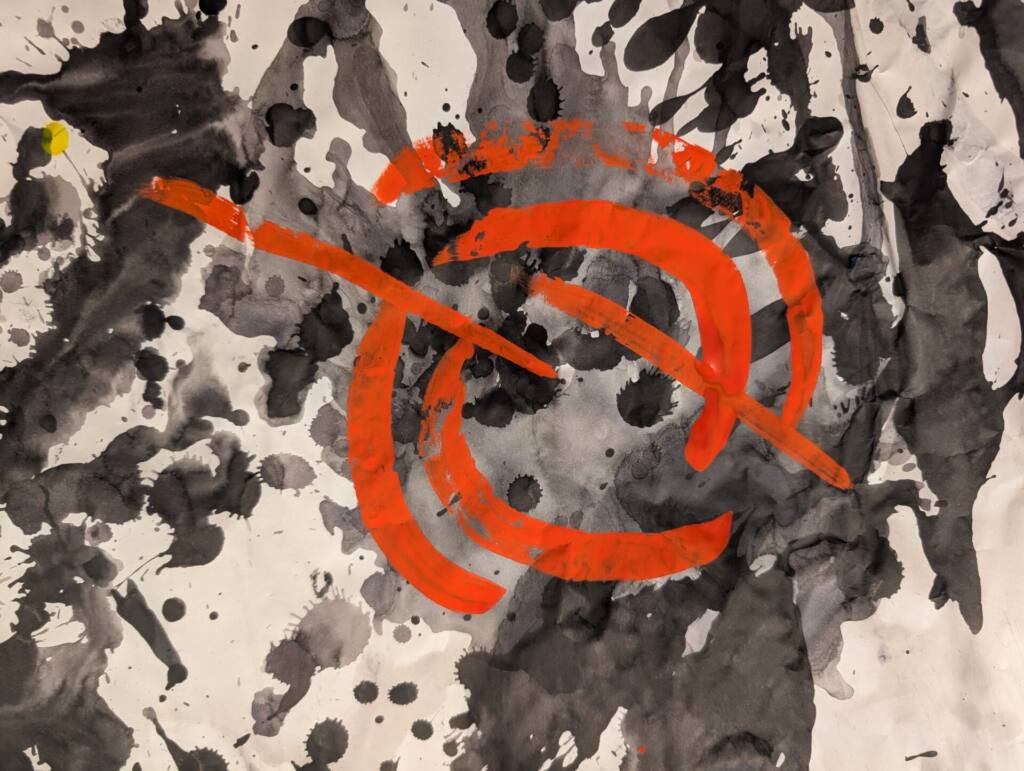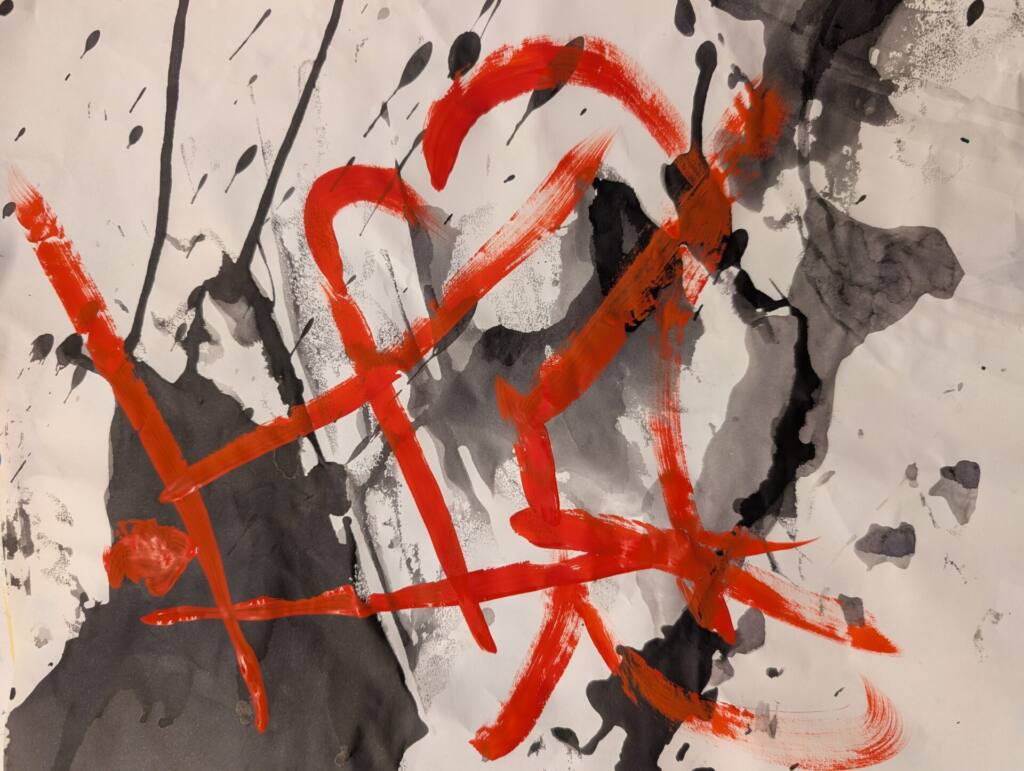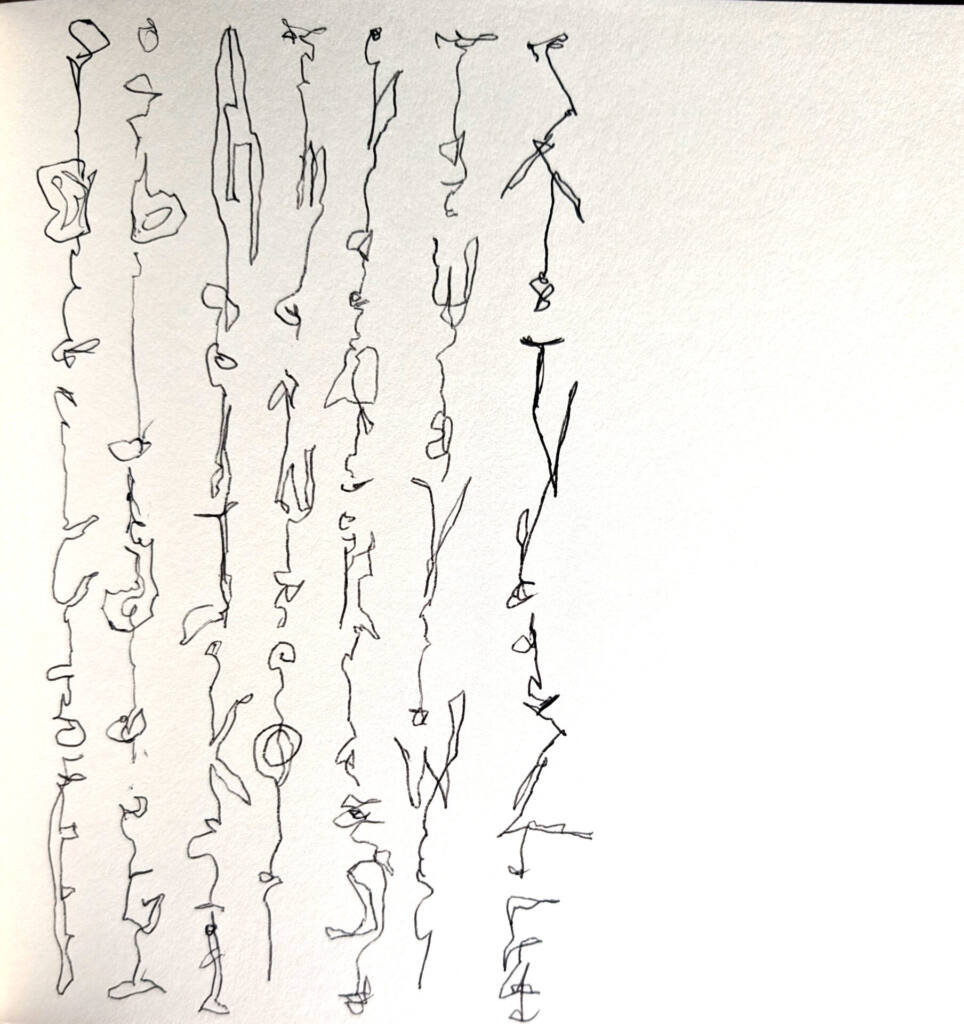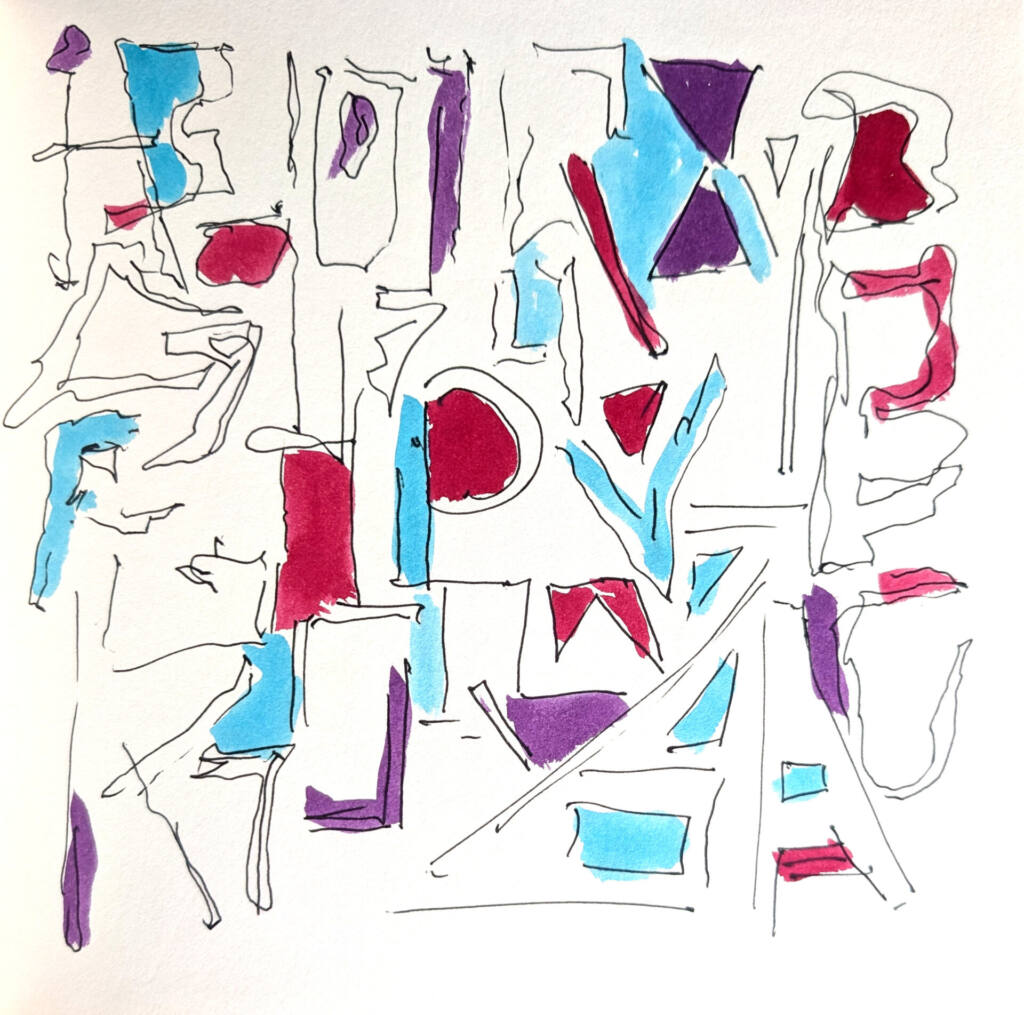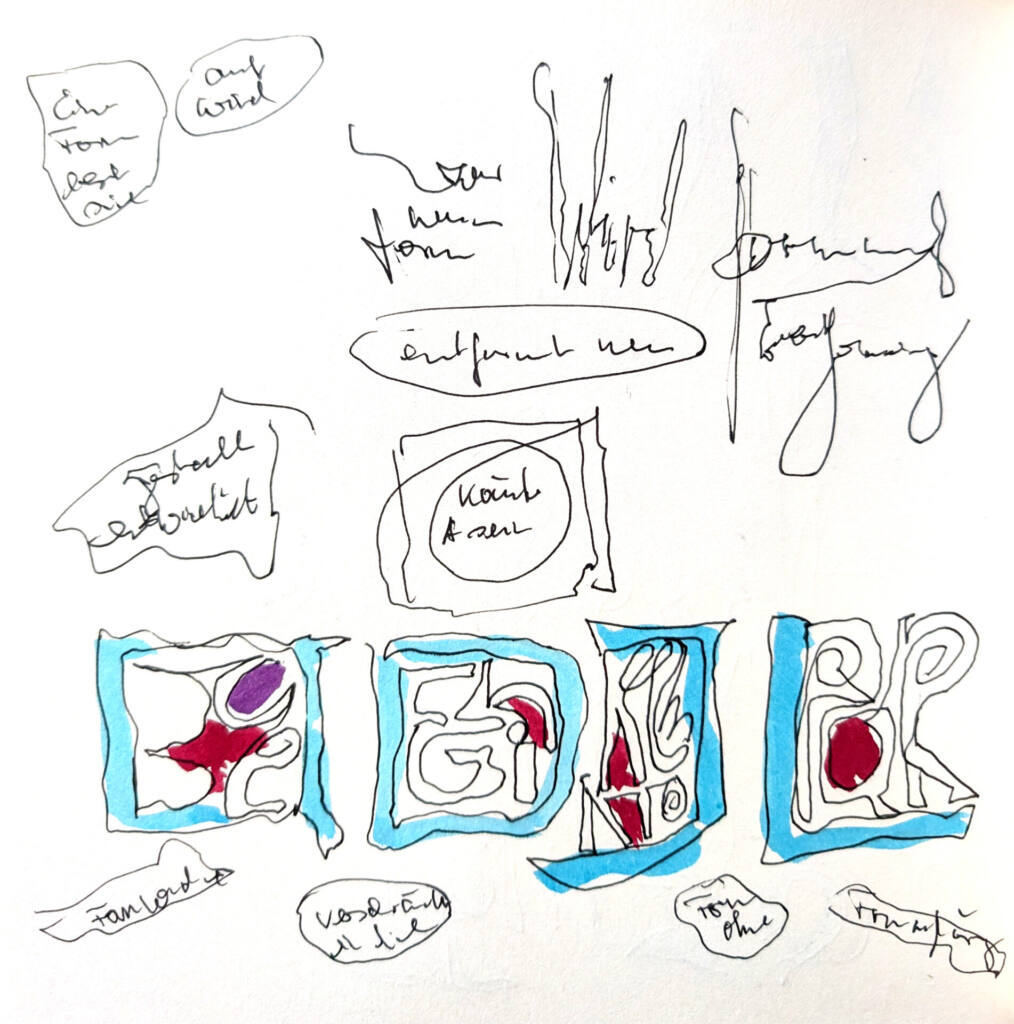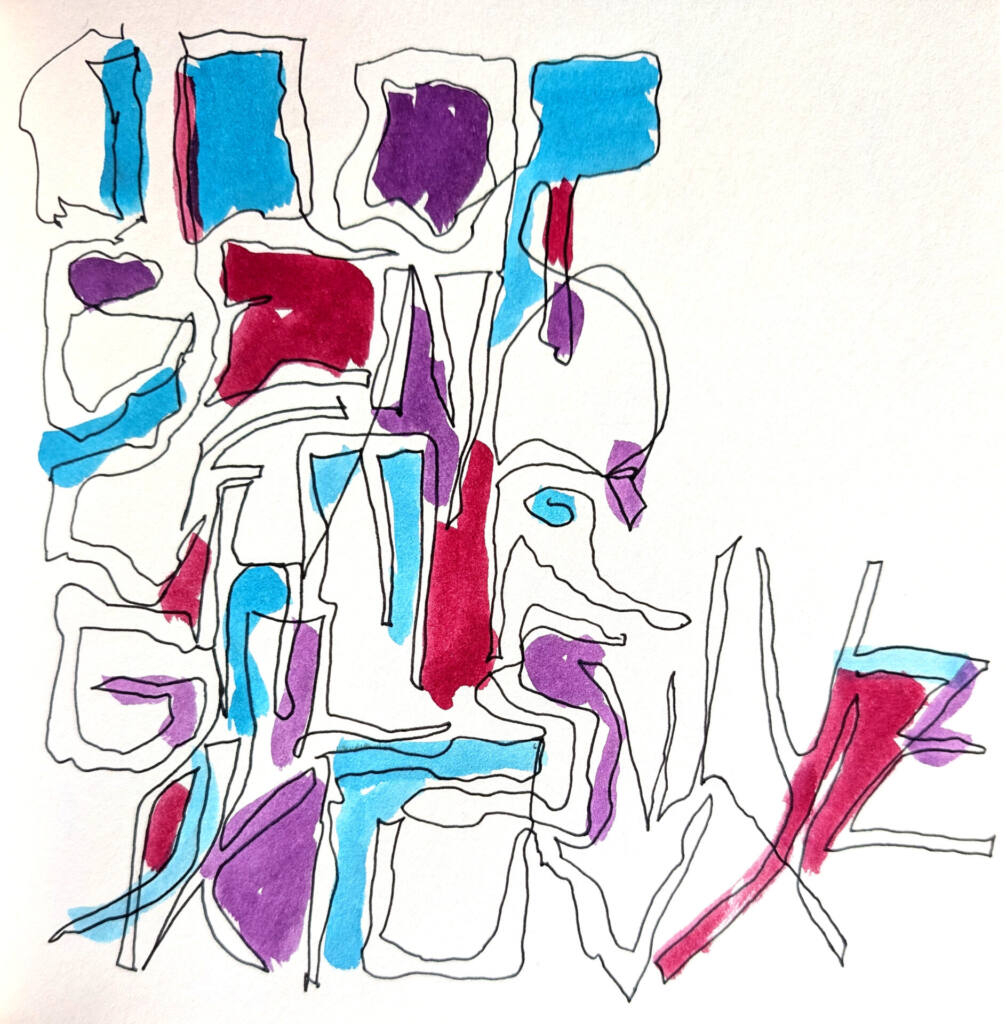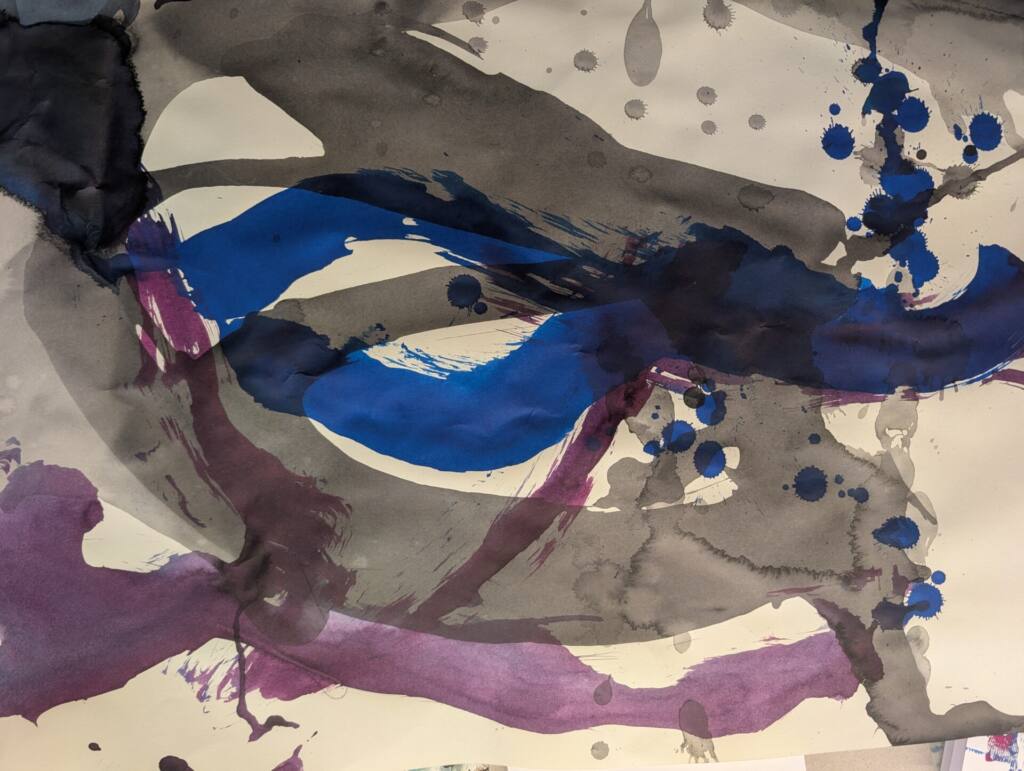
Formwerdung und Formauflösung
Vom Zufall und der Ordnung
Formen wachsen zusammen, verbinden sich, werde zur Gestalt, lesbar oder versteckt nur zu erraten. Verbindungen, Strukturen, offen und verschränkt. zeichenhaft und symbolisch. Es entwickeln sich Strukturen, die mehr nach Neugliederung, nach Erkennbarkeit, nach bekannten Zeichen rufen. Vielleicht war da noch eine Anmutung von Bedeutung, aber gelöst von einer bekannten Form.
Wir verwenden Papiere, die durch das Malen, Spritzen, Wischen mit großen Pinseln entstanden sind und verarbeiten sie weiter. Wir verwenden Sie für Überschreibungen und farbige Bemalungen, lassen neue Kompositionen entstehen.
Wir fassen sie in einem Buch oder Leporello und füllen es mit neuen Gedanken, die ebenfalls Formwerdung und Formauflösung erleben.